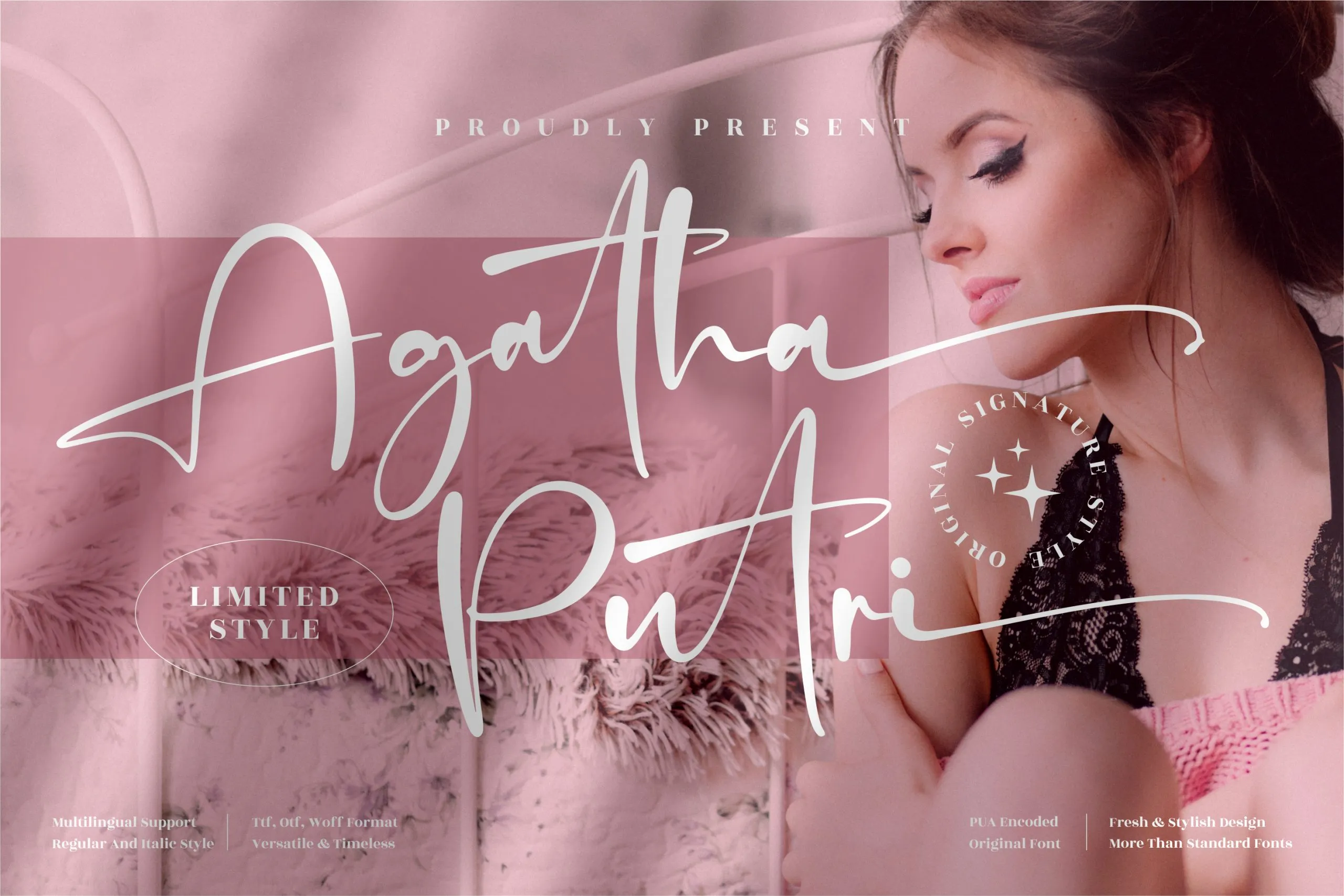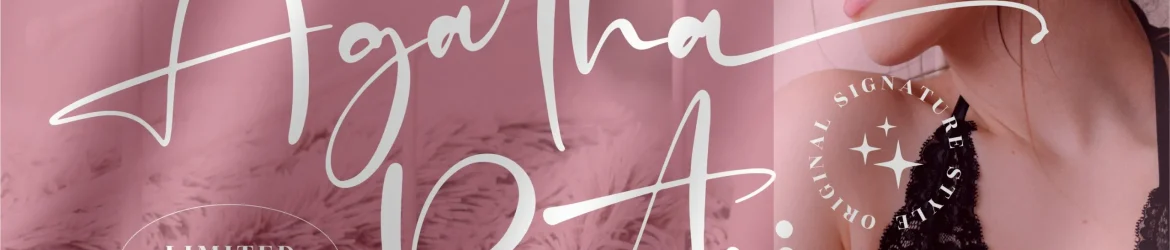
Agatha Putri Font – Download Grátis
A Agatha Putri Font é uma elegante fonte para assinatura, criada pelo designer perspectype Studio. Perfeita para projetos de alta qualidade que exigem um toque sofisticado e personalizado, como logotipos, materiais de marcação, embalagens de produtos, mugs decorativos, cartões de agradecimento, pacotes de livro, cardapios e até mesmo sobrelistas. Este fonte é especialmente versátil, adequada para todos os tipos de projetos que buscam um toque refinado e único. Ideal tanto para criar uma identidade visual forte quanto para adicionar gráficos personalizados a qualquer projeto de design. Seja você um designer ou criativo de materiais de consumo, Agatha Putri Font é sua fonte perfeita para trazer o seu trabalho à próxima elevação.